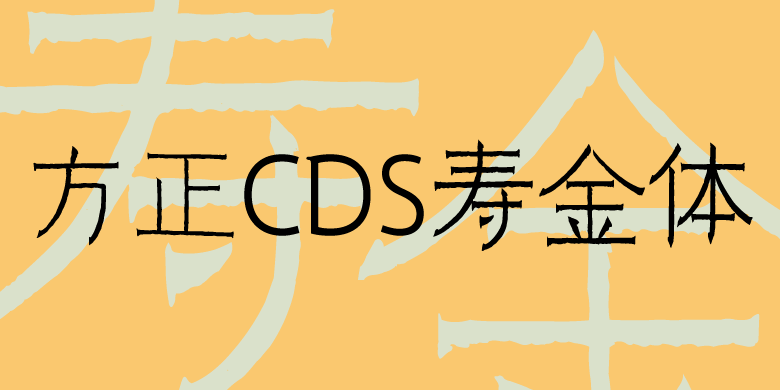
方正CDS寿金体
耿荫河
隶书、常规书写·毛笔
CDS设计师沙龙作为一个公益组织一直以来致力于对中国传统文化美学研究与探索。艺术家耿晓刚先生多年尝试将中国积累沉淀的书法艺术文化推陈出新,面向当下想确立其新价值新意义。他亲笔的CDS寿金体就是将扬州八怪之首金农的书法楷书与隶书特点融合,以现代人眼光再次呈现于当下。此书体特点横细笔画均匀布局,风格规整,笔划沉厚朴实,其笔划收锋结构严密,多内敛之势,而少外拓之姿。奇简约明快给人已舒朗雅致之气息,同时又不失灵秀。秀在骨,韵在笔外,耐人寻味。从美学角度来看,其书体形态具有一种典型的规整沉稳又不失灵秀的特质,同时此书的特性也合乎当下的审美趋势,其字形也较符合一些作为内文、排版、艺术特性的一些字体选择。 CDS除了一直致力于设计行业内外的经验分享与学术交流外,还踊跃探索东方语境下的文化美学,积极寻找其中的设计价值和哲学意义;本次CDS寿金体的设计,就是从中国书法文化中挖掘瑰宝,并结合当代审美理念,进行重新创作设计,将中国的书法文化传承、创新与发扬光大。